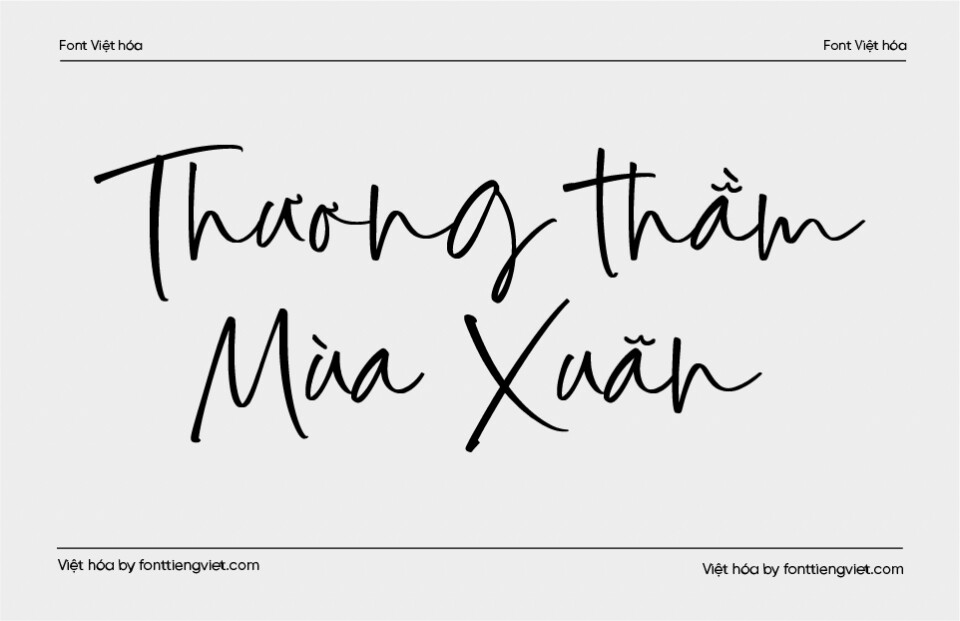
Giới thiệu về Font Việt hóa 1FTV VIP Apricote Smoothie
Trong thế giới thiết kế đồ họa hiện đại, việc lựa chọn một Font Chữ phù hợp đóng vai trò quyết định đến tính thẩm mỹ và thông điệp của sản phẩm. Font Việt hóa 1FTV VIP Apricote Smoothie là một bộ phông chữ mang phong cách ngọt ngào, mềm mại, lấy cảm hứng từ những ly sinh tố mơ mát lạnh. Đây là lựa chọn hoàn hảo cho các bạn học sinh và giáo viên khi muốn trang trí bài thuyết trình hoặc làm báo tường sinh động.
Đặc điểm nổi bật của bộ phông chữ
Bộ Font Việt hóa 1FTV VIP Apricote Smoothie sở hữu những đường nét uốn lượn tự nhiên, tạo cảm giác gần gũi và đầy năng lượng sáng tạo. Điểm đặc biệt của phiên bản này là đã được tối ưu hóa bảng mã tiếng Việt, giúp người dùng gõ dấu chuẩn xác mà không lo bị lỗi hiển thị. Phông chữ này cực kỳ phù hợp cho các thiết kế thiệp mời, bìa sách thiếu nhi hoặc các biển bảng trang trí lớp học thêm phần bắt mắt.
Cách ứng dụng Font Việt hóa 1FTV VIP Apricote Smoothie hiệu quả
Để khai thác tối đa vẻ đẹp của Font Việt hóa 1FTV VIP Apricote Smoothie, bạn nên sử dụng chúng cho các tiêu đề lớn hoặc các đoạn trích dẫn ngắn. Sự kết hợp giữa tông màu pastel nhẹ nhàng và định dạng chữ viết tay sẽ giúp tác phẩm trở nên chuyên nghiệp hơn. Ngoài ra, phông chữ này còn hỗ trợ tốt trên nhiều phần mềm đồ họa phổ biến, giúp việc sáng tạo trở nên dễ dàng và nhanh chóng đối với mọi đối tượng người dùng.
Kết luận về bộ phông chữ độc đáo